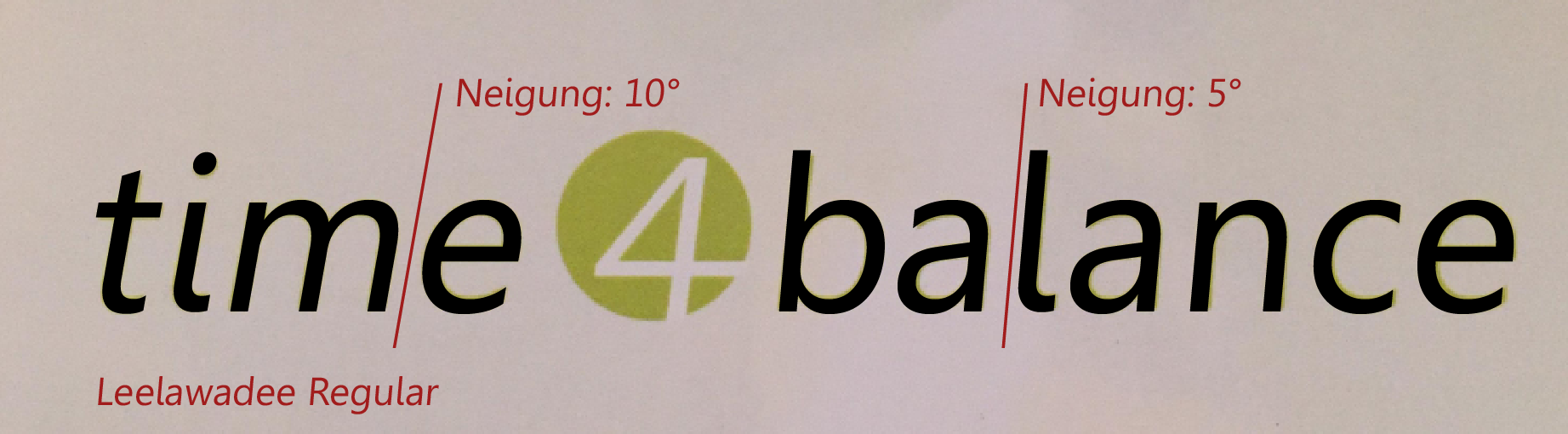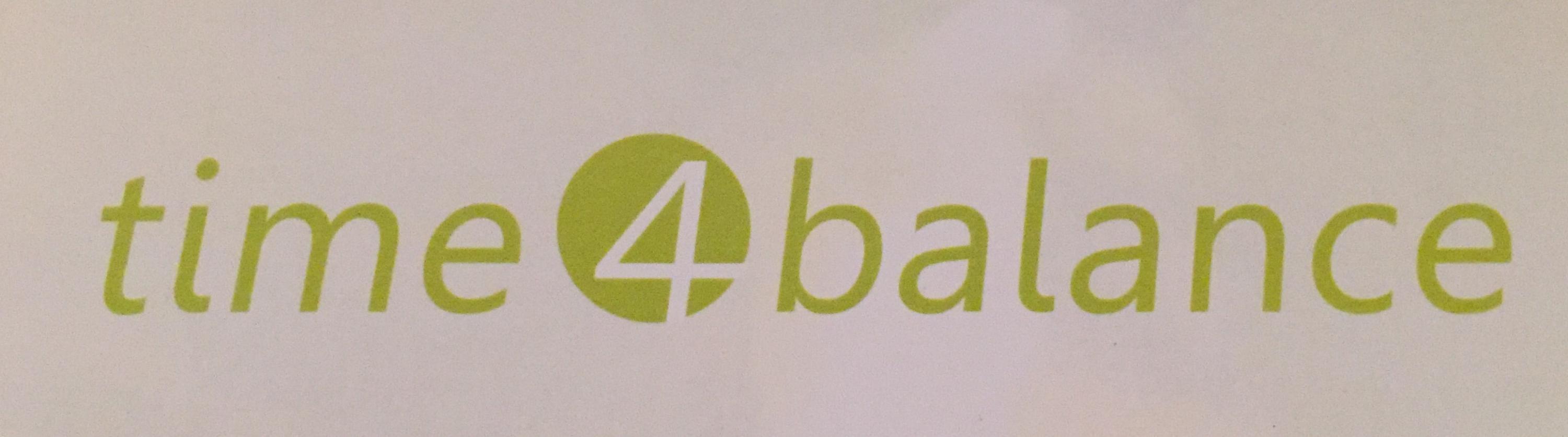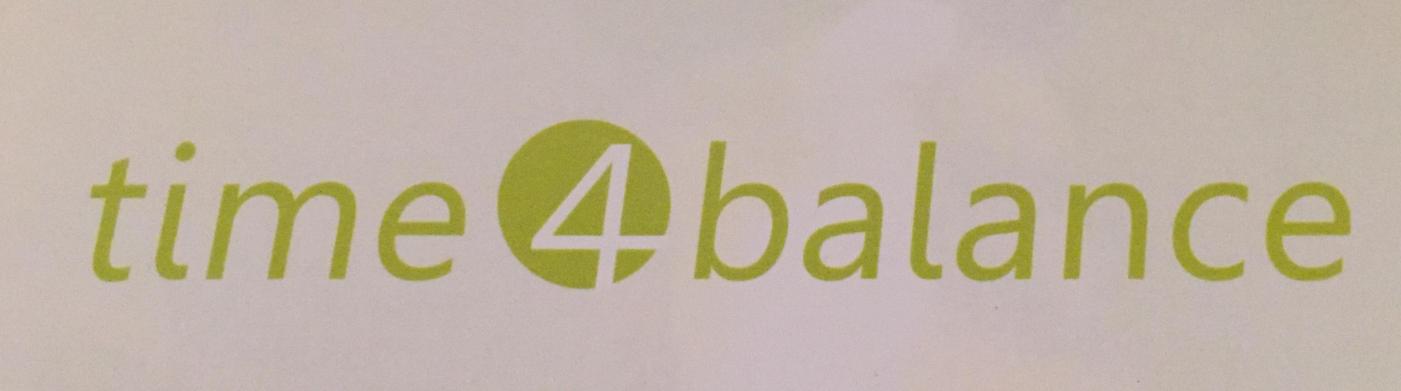
Woher stammt das? Gibt’s noch mehr zu sehen außer dem verzerrten Logo?
Da die Buchstaben ja bis auf "l" und "i" schon verdammt nach Frutiger bzw. nach Frutiger-Verwandschaft aussehen, habe ich den Font Segoe UI mal dagengehalten, der ja – weil auf den meisten Windows-Rechnern standardmäßig installiert – immer gut als Ersatzschrift für Frutiger bzw. Myriad passt. Über den Wikipedia-Eintrag der Segoe UI bin ich dann über die Schriftart Leelawadee gestolpert – mir als Mac-Benutzer bis dahin nicht bekannt. In diesem thailändischen Font sind die lateinischen Buchstaben fast identisch mit der Segoe UI – bis auf  „ … die Großbuchstaben »I« und »M« sowie die Kleinbuchstaben »i« und »l«) …“.
Beim Drüberlegen passt das aber schon ganz gut – ich gehe mal davon aus, dass bei dem Logo die Buchstaben künstlich geneigt (sagt man das so?) wurden.